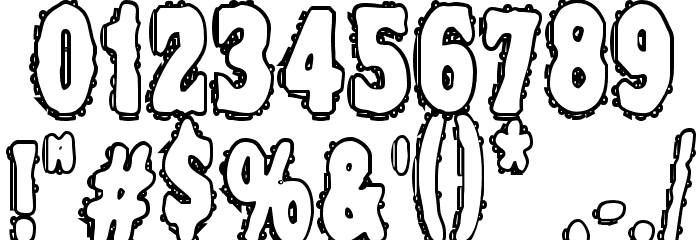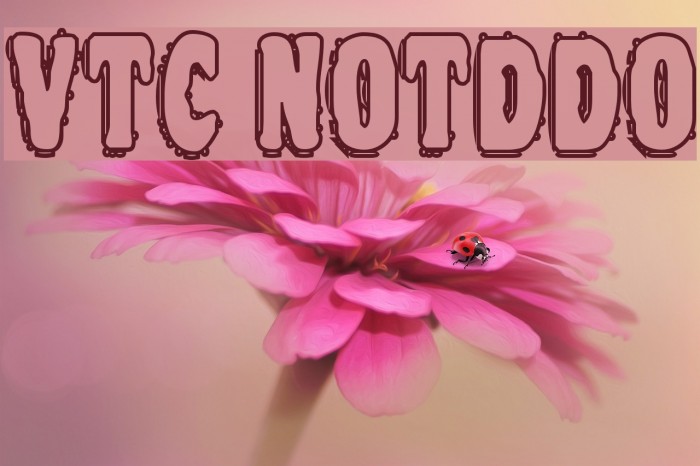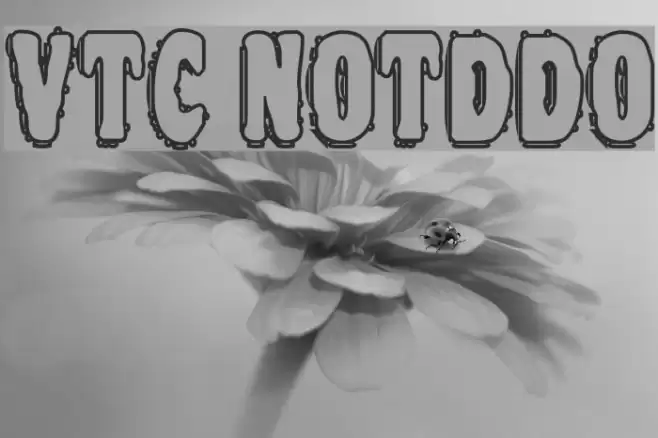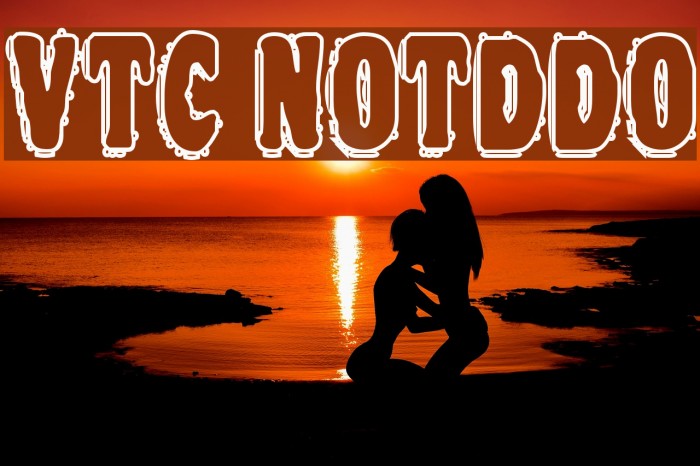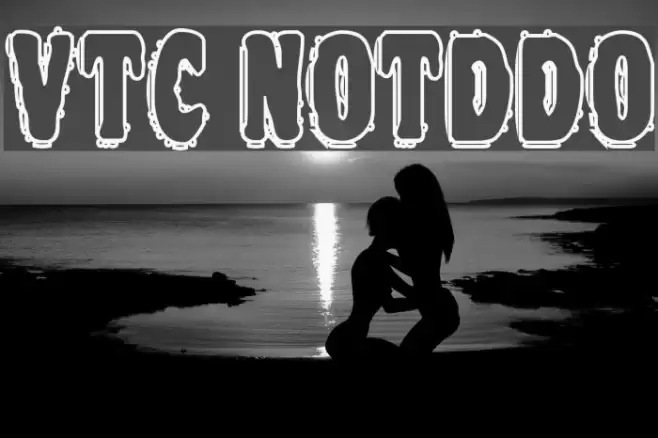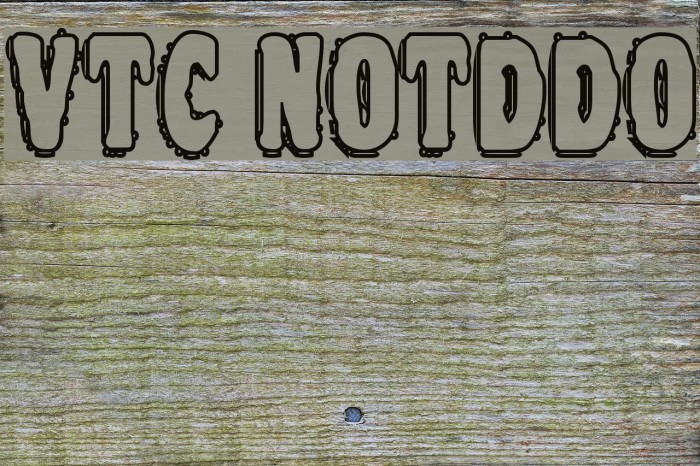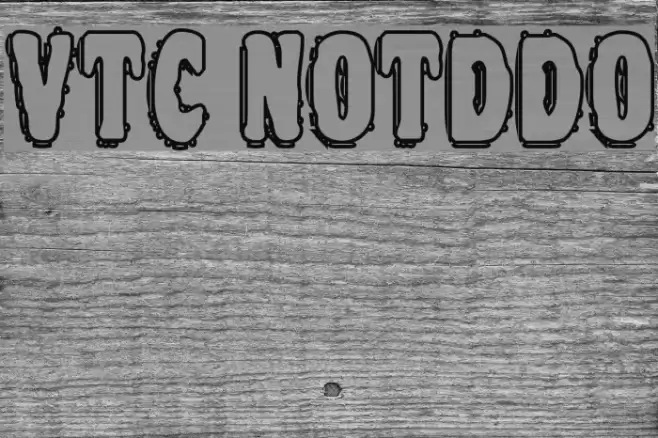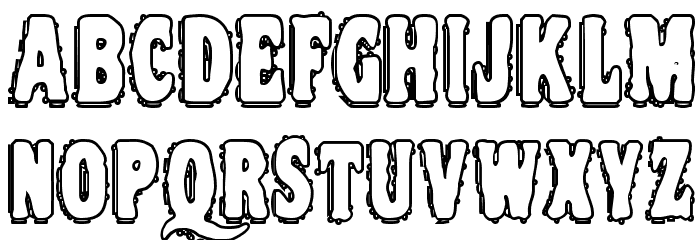
VTC NightOfTheDrippyDeadOuttie Font
| مشاريع مقترحة | Ideal for Halloween-themed posters, party invitations, horror movie titles, and spooky event branding. |